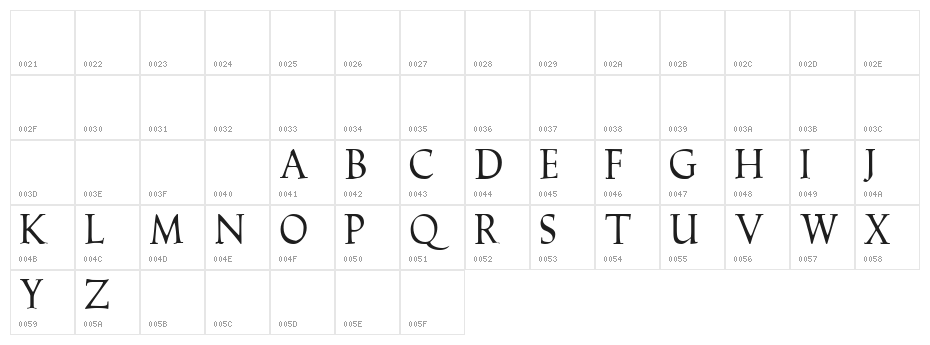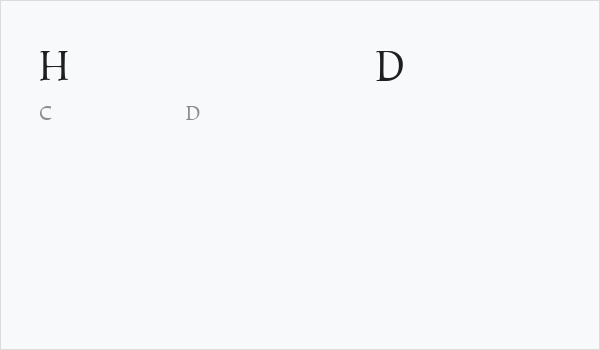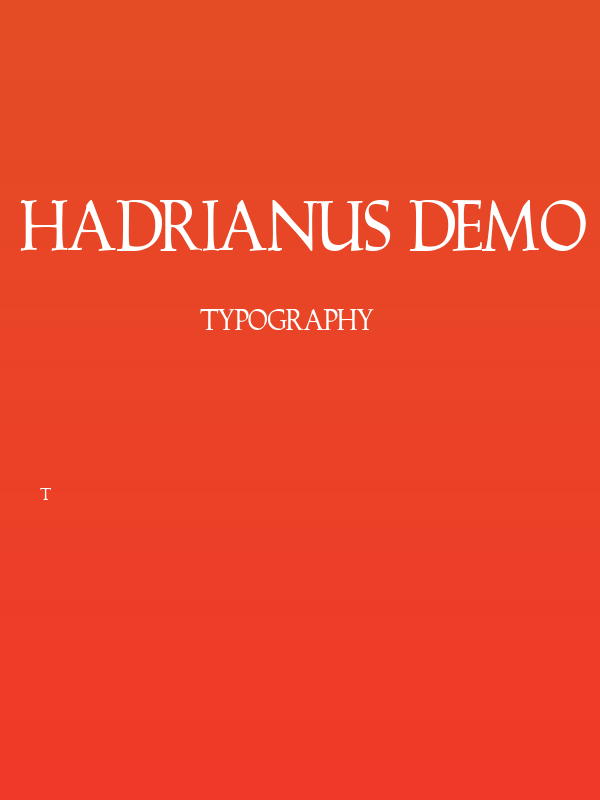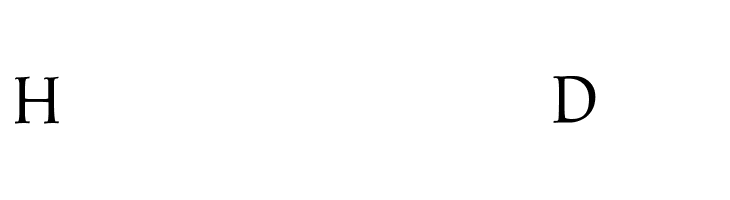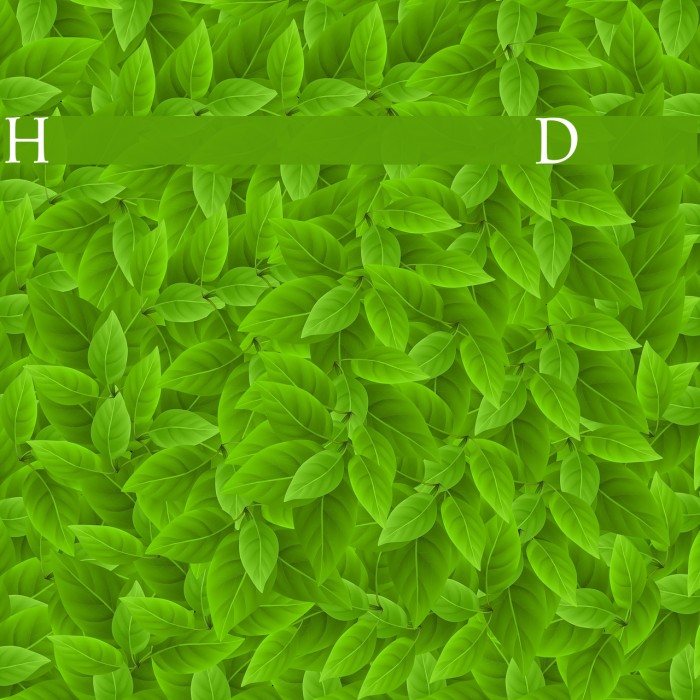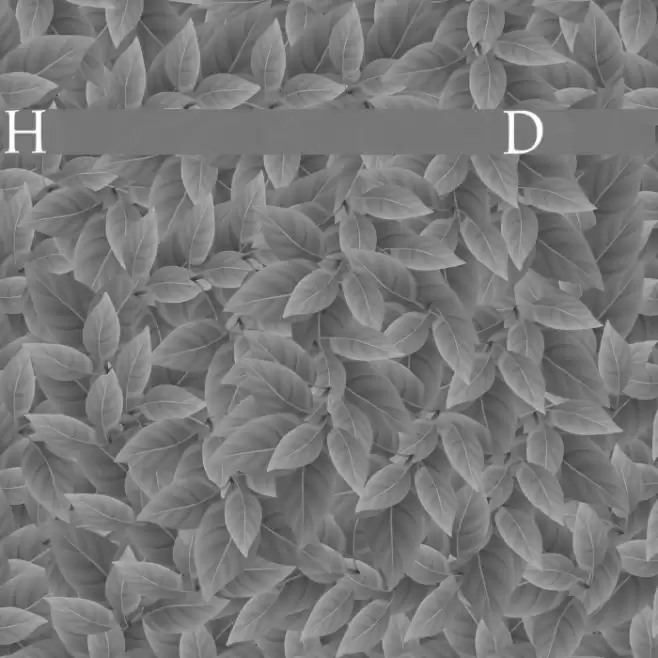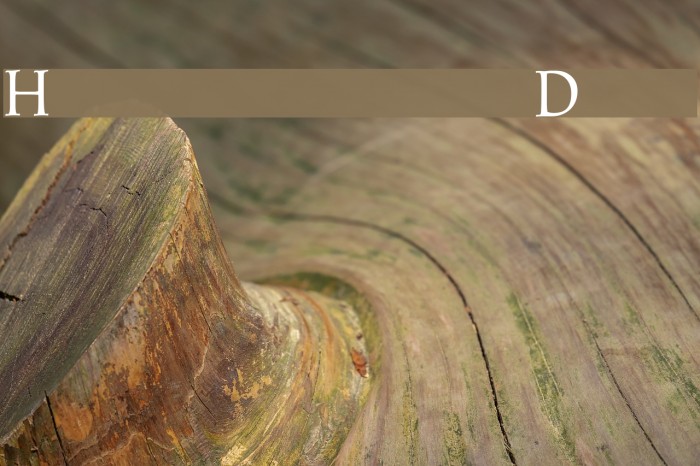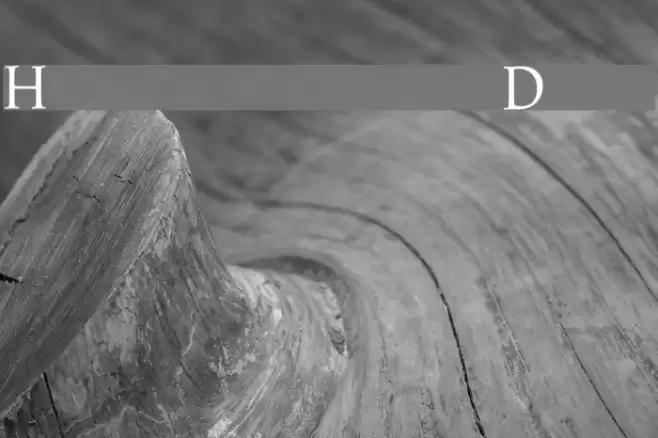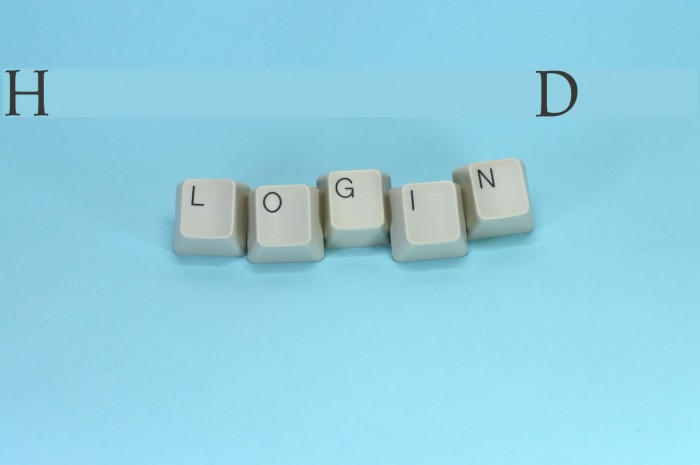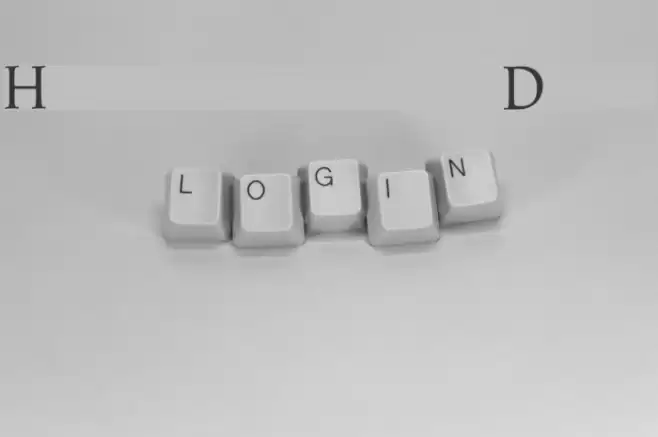
Hadrianus Demo Font
| Caso d'uso | Headlines, Logos, Formal Invitations |
| Progetti proposti | Ideal for formal invitations, historical documents, branding with a heritage theme, and elegant signage. |